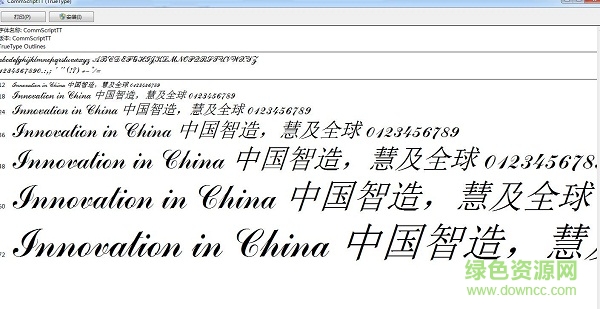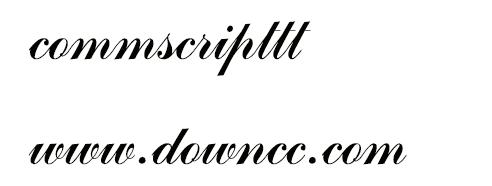
軟件介紹 軟件標(biāo)簽: 英文花體 英文字體 commscripttt italic字體是一款傾斜的英文花體字體,可用于文章標(biāo)題、書籍、書信等方面,綠色資源網(wǎng)還有更多漂亮的斜體字體和花體字體可供下載,歡迎前來體驗!字體推薦【長牟體】實際上是長形宋體,常用于書籍標(biāo)題和報紙標(biāo)題。長牟體 授權(quán):免費軟件 WinAll, WinXP, Win7大?。?.4M語言:中文長牟體字體是一款清秀美觀的特色中文字體,舒展勁挺不拘謹(jǐn),字形修長,和姚體字體有一點像,特征非常鮮明,適用于報刊、書籍的標(biāo)題字,有需要者歡迎下載!常見電腦字體介紹【圓體】Windows中的圓體字主要是四通公下載地址【彩云體】此副字是美術(shù)體字,是以同一粗細(xì)線條勾勒的輪廓字。筆畫的中間留出空白,似一朵朵浮云hyl1gj 授權(quán):免費軟件 WinAll, WinXP, Win7, Win8, Win10大?。?.1M語言:中文hyl1gj字體(漢儀彩云體簡)是一款新穎獨特的空心字體,該字體筆畫清晰,飽滿圓潤,具有很好的裝飾作用,廣告、雜志、海報、網(wǎng)頁都可以使用這款個性字體,喜歡的朋友快來下載吧!空心字介紹空心字,又名雙鉤書法。雙鉤下載地址commscripttt字體安裝方法方法一:控制面板/字體/文件/安裝新字體;方法二:直接將字體復(fù)制到C:\WINDOWS\Fonts。方法三:針對win7系統(tǒng),用戶只需選中字體右鍵安裝即可。 軟件截圖 上一張下一張(1 / 1) 安裝詳細(xì)截圖 其他版本下載 標(biāo)題 大小 更新日期 下載 下載地址 電腦版 commscripttt italic字體 點擊報錯 軟件無法下載或下載后無法使用,請點擊報錯,謝謝! 關(guān)閉報錯反饋 請描述您所遇到的錯誤,我們將盡快予以修正,謝謝! *必填項,請輸入內(nèi)容 本類最新 sounso beauty字體 spyced哥特英文字體 ttf版 zerodegrees字體 the next font ttf版 coolvetica font keep calm ttf 免費版 相關(guān)文章 Apache的ReWrite的應(yīng)用 XML Schema學(xué)習(xí)筆記 Apache之AllowOverride參數(shù)詳解 錯誤 2812: 未能找到存儲過程 'master.dbo.xp_fixeddrives' ACCESS數(shù)據(jù)庫沒有寫入權(quán)限導(dǎo)致ADODB.Recordset 錯誤 '800a0cb3'的解決辦法 無法載入 mcrypt 擴展,<br />請檢查 PHP 配置終極解決方案 用戶評論 熱門評論 最新評論 發(fā)表評論 查看所有評論(0) 昵稱: 請不要評論無意義或臟話,我們所有評論會有人工審核. 字?jǐn)?shù): 0/500 (您的評論需要經(jīng)過審核才能顯示)